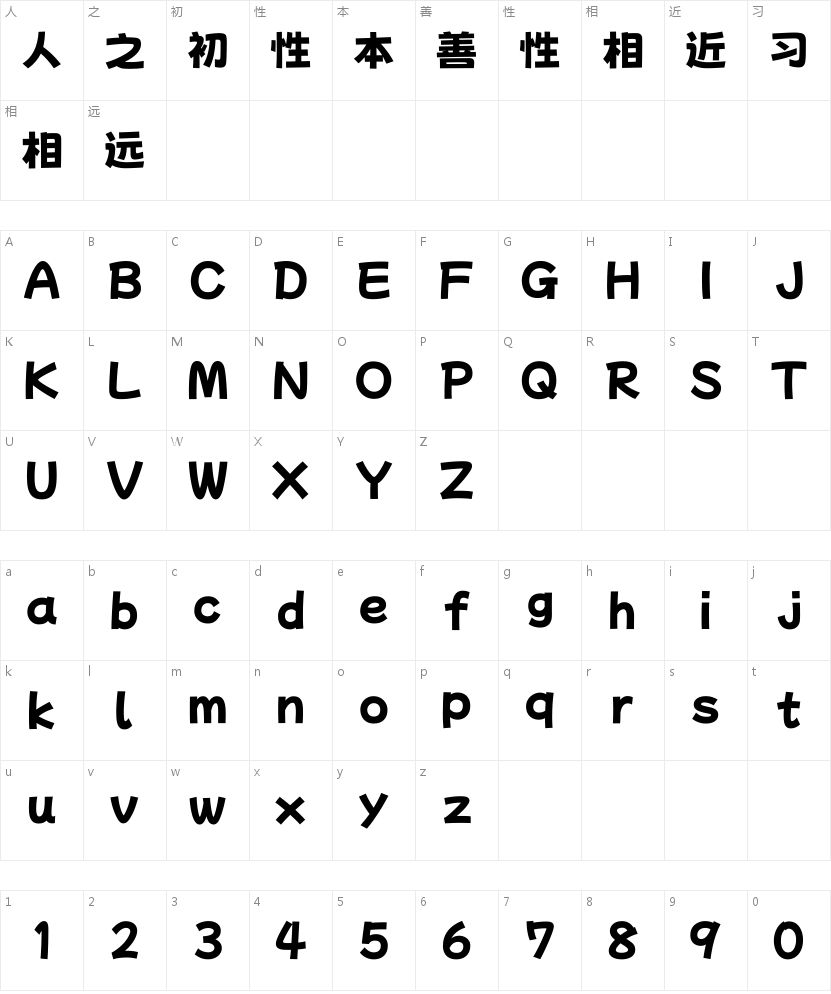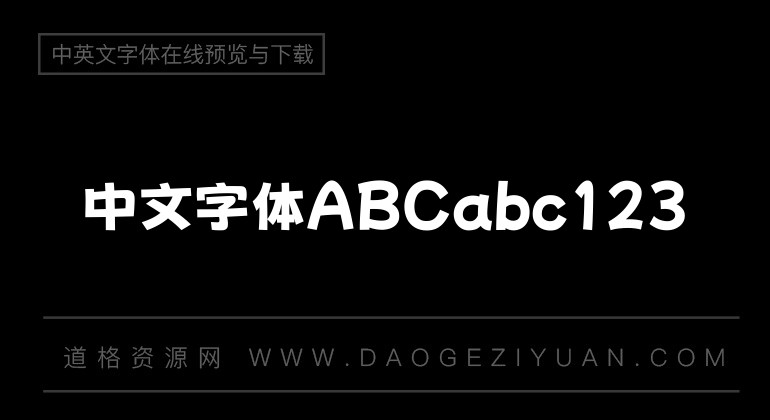
荆南波波黑字体是一种免费的中文字体,由中国设计师江波波(Jiang Bobo)设计。该字体是一种无衬线字体,具有现代感和科技感,适合用于各种设计和创意项目中。荆南波波黑字体的特点是线条流畅,笔画粗细均匀,同时具有较高的可读性和易用性。该字体支持多种不同的字重和风格,可以满足不同需求的用户的需要。文件名:BOBOHEI-2.otf
荆南波波黑是一款非常不错的手写艺术字体,具有很好的视觉感,适合于文化类的宣传设计、商业类品牌的广告和产品包装设计以及个性化文字排版等较多场景。